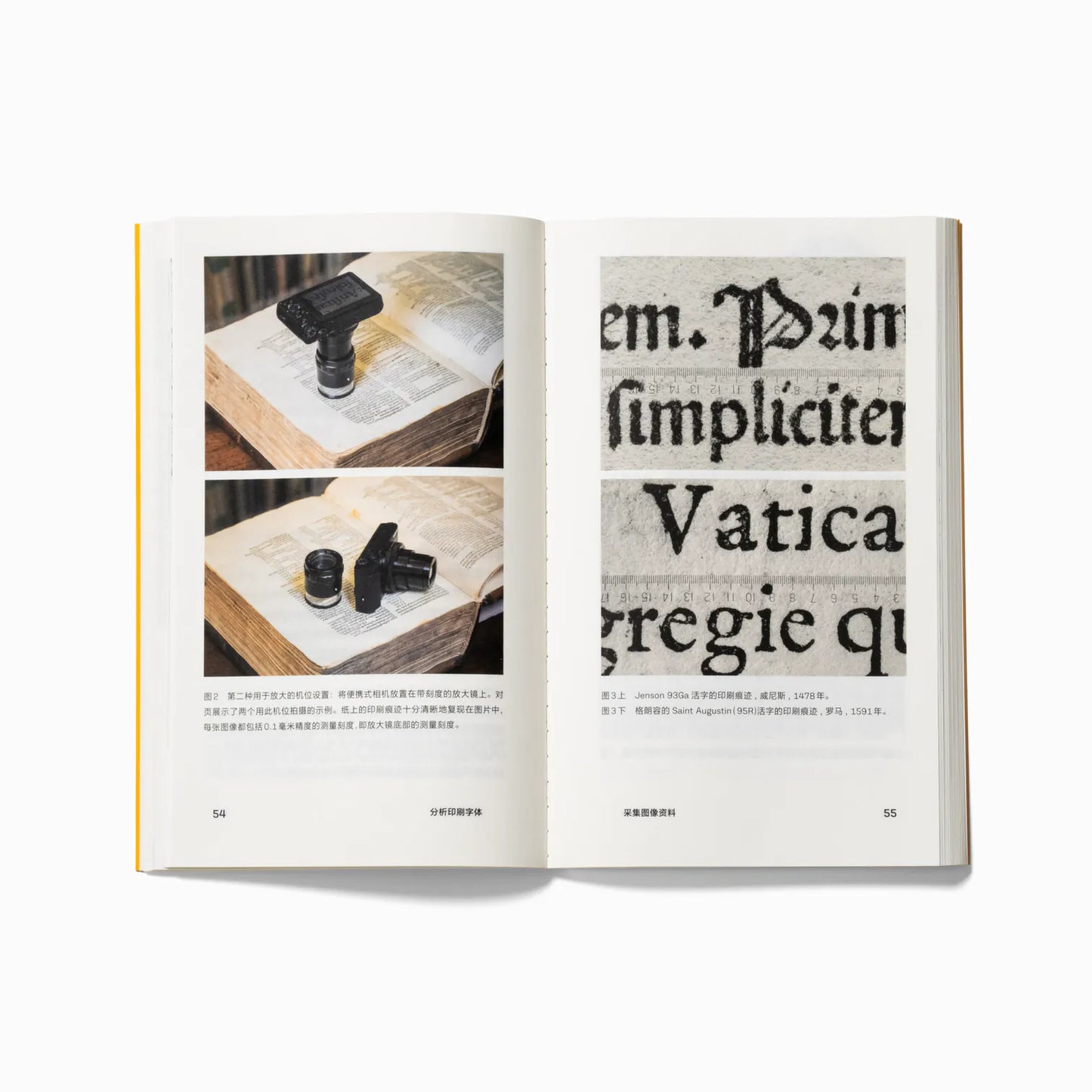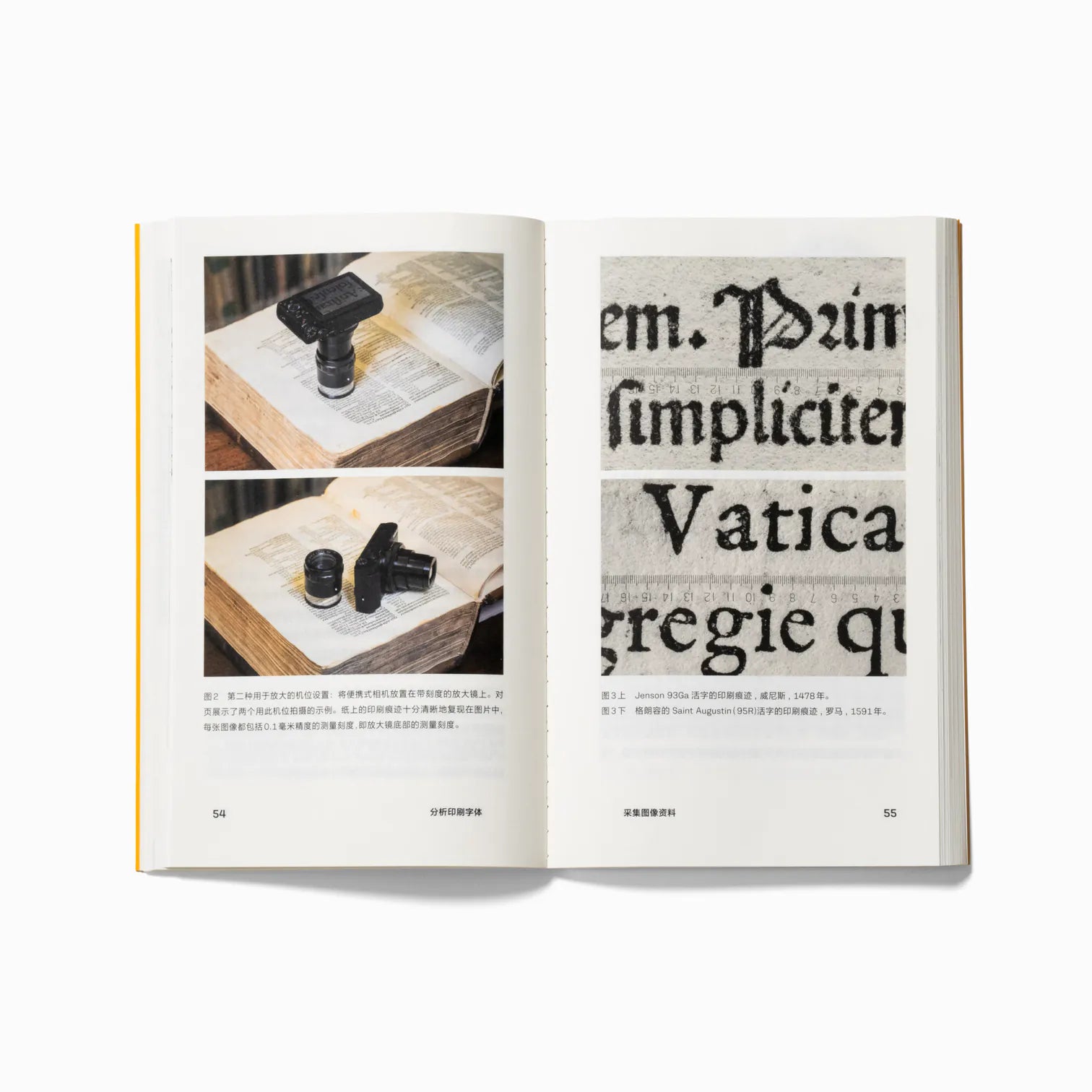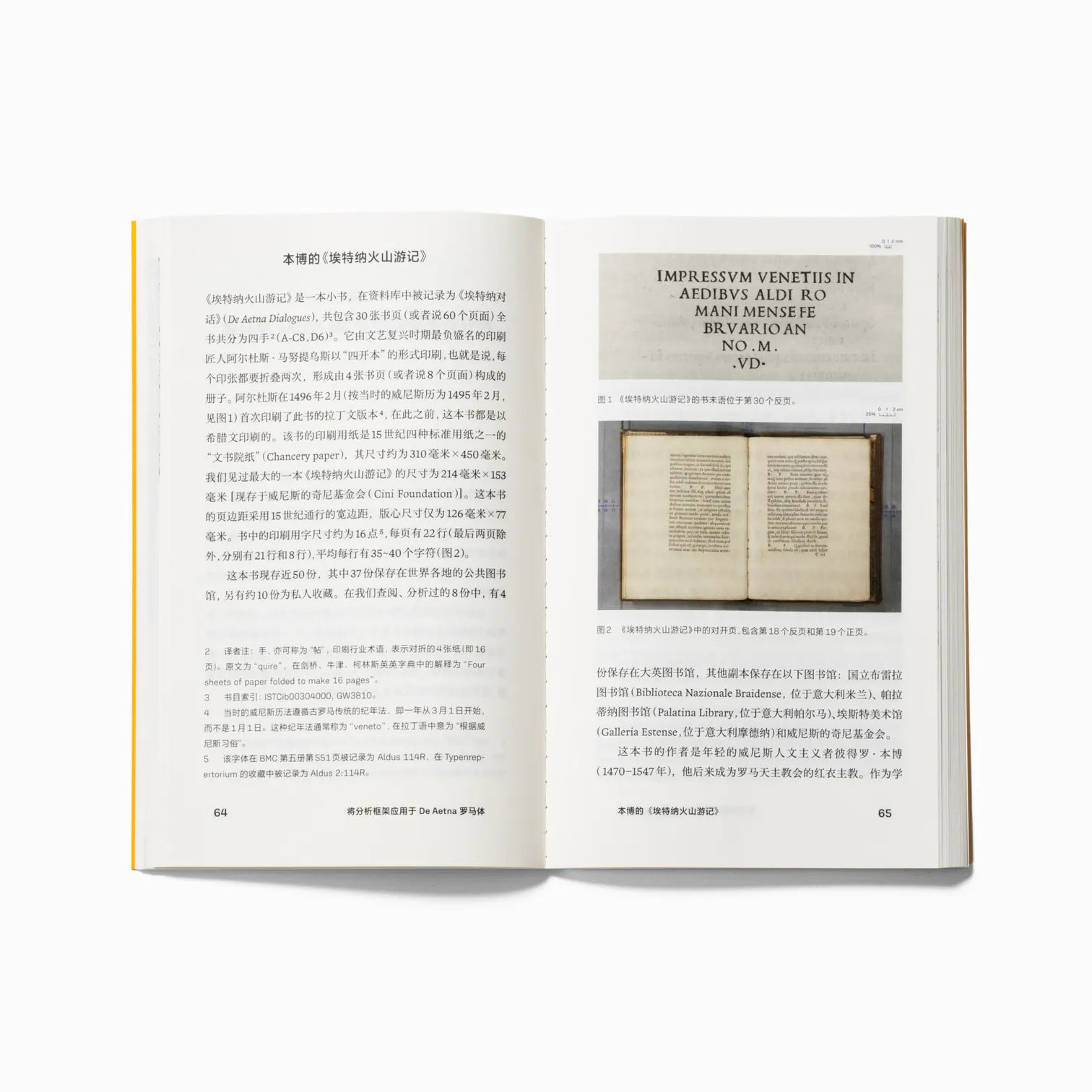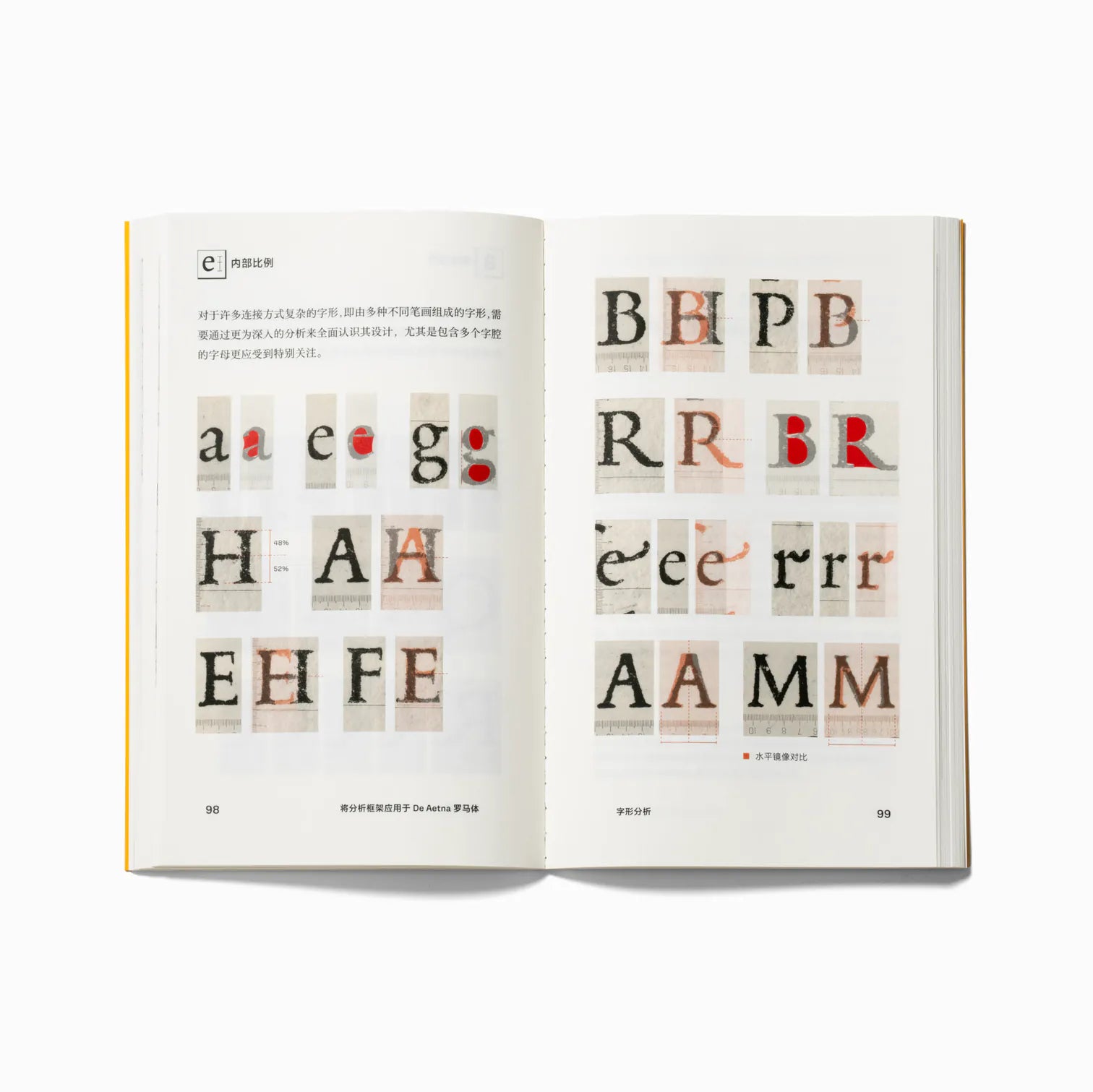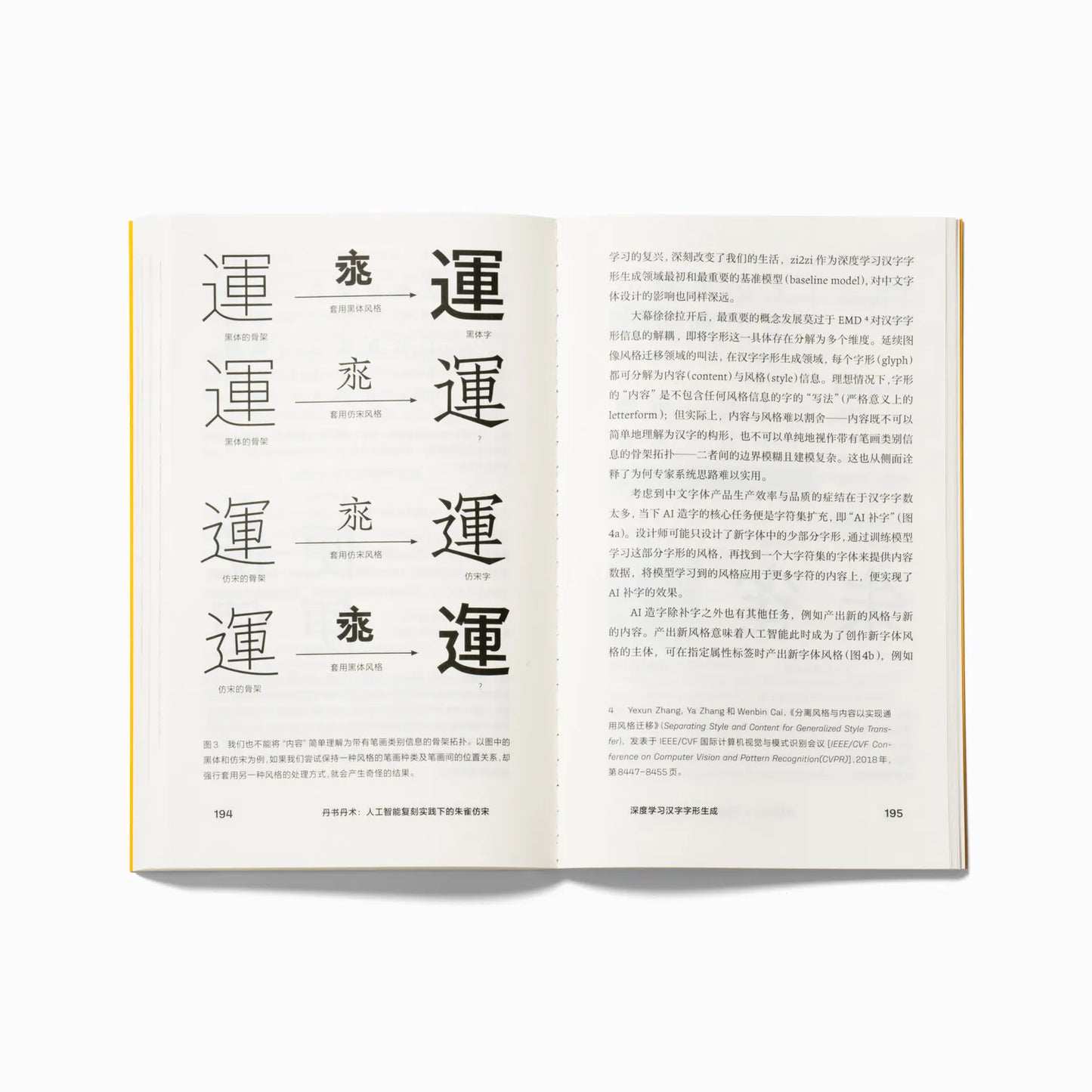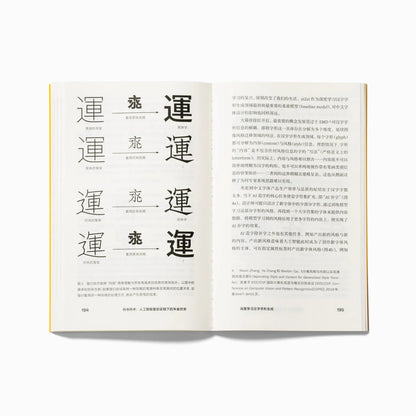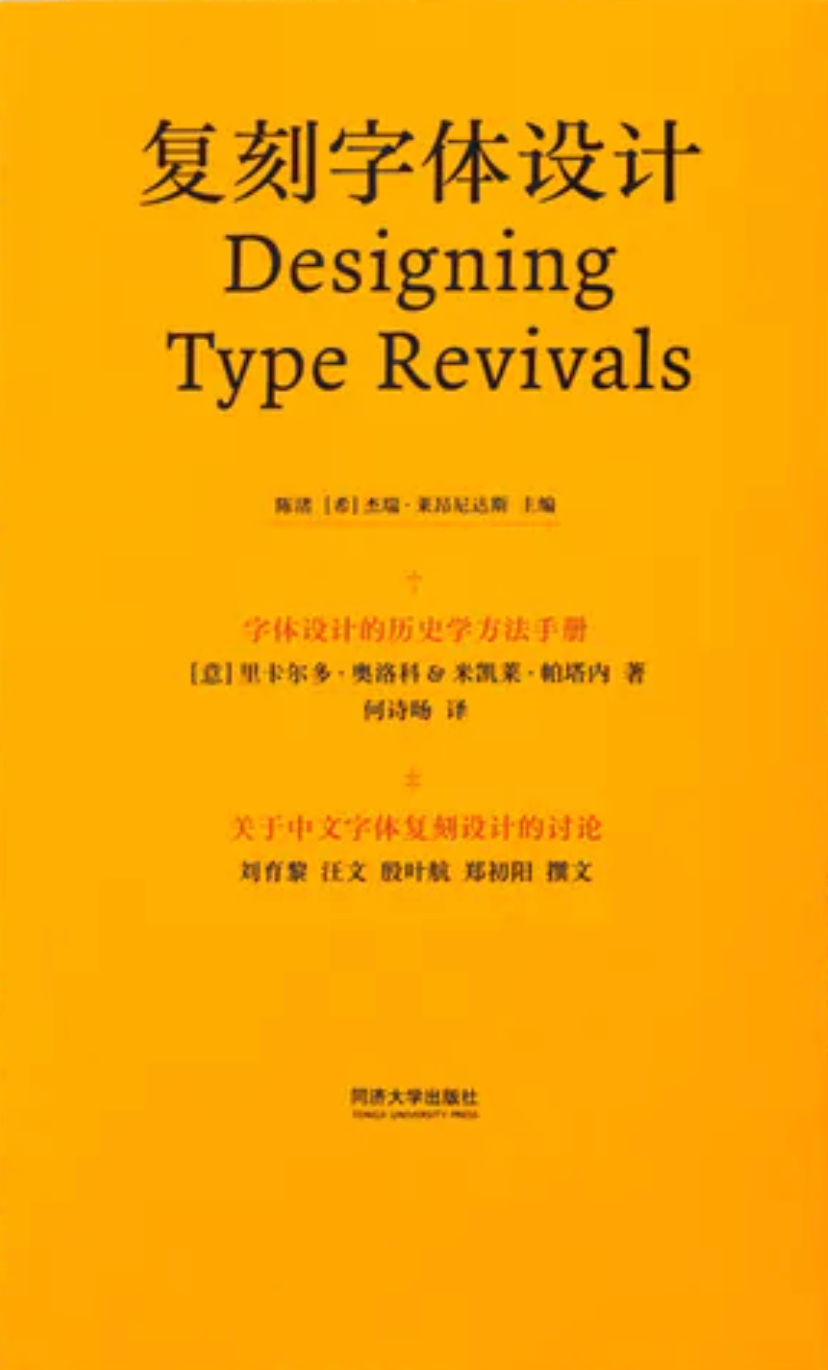
復刻字體設計:字體設計的歷史學方法手冊
數以百萬計的雕版、活字既是印刷史的遺珍,也是當代字體設計的超大素材庫,在現代社會仍然保有鮮活的藝術價值。以歷史為藍本,通過嚴謹規範的覆刻和再設計,豐富當代字體環境、探索字體設計演變和創新的可能性,使古籍或鉛字中的字體在當今的印刷與排版環境下重煥生機,成為全球字體設計界的共識。為了總結過去在覆刻字體設計與研究中的想法和實踐流程,來自雷丁大學的字體設計學者里卡爾多(Riccardo Olocco)與米凱萊(Michele Patanè)撰寫了《復刻字體設計:字體設計的歷史學方法手冊》(Designing type revivals: Handbook for a historical approach to typeface design)一書,充分闡釋了深入研習字體和字形史的標準化方法,並將其應用於拉丁字母的設計中。希望通過此書,構建出一種易於覆制的實踐模式,並激勵後續的從業者、學生和學者開展更深入的批判性思考。
《復刻字體設計:字體設計的歷史學方法手冊》一書凝結了資深字體設計師、教師多年的研究、實踐和工作坊教學經驗,是一本西文字體覆刻設計的實用指南。它從理解覆刻概念的精髓出發,以作者的真實設計項目——De Aetna羅馬體的覆刻為線索,引導讀者系統掌握從採樣藍本字形、 分析字形量度到製作計算機字體的覆刻字體設計方法論。本書中文版由notadesign主理人陳渚及雷丁大學排版學教授、方正獎拉丁組評審傑瑞·萊昂尼達斯(Gerry Leonidas)主編,方正字庫字體設計師何詩暘擔任翻譯。
《復刻字體設計:字體設計的歷史學方法手冊》中文版特別邀請了劉育黎、汪文、殷葉航、鄭初陽等四位知名中文字體設計師撰文,共同探討中文字體覆刻的實踐經驗,形成了「中文字體覆刻設計的討論」這一專題。在本書中,方正字庫設計總監汪文以方正漢文正楷的覆刻為例,深入剖析了漢字覆刻設計中所面臨的技術與藝術挑戰。